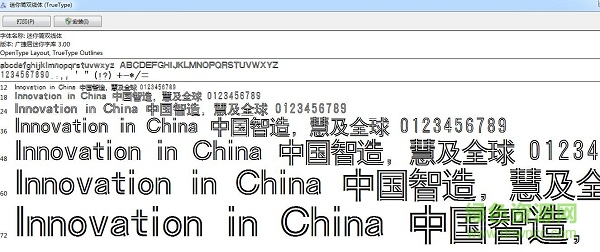
jsuanxian
jsuanxian字體是一款個(gè)性十足的迷你簡(jiǎn)雙線體字體,所有線條都是雙層,黑白均勻,結(jié)構(gòu)端正,非常醒目,適合用在各種廣告設(shè)計(jì)方面,有需要者歡迎免費(fèi)下載!
字體的筆畫(huà)差異
筆畫(huà)是字體構(gòu)成最基本的單位,筆畫(huà)的設(shè)定對(duì)于字體性格的表現(xiàn)也尤為重要,是線段還是塊面即使相同的字也會(huì)給人截然不同的感受。
jsuanxian
【曲vs直】
就像自由體操和拳擊,一個(gè)柔美靈活,一個(gè)剛勁力量。在字體里面,筆畫(huà)以曲線為主的話,就會(huì)給人飄逸柔和的感覺(jué),相反筆畫(huà)直來(lái)直往,包括轉(zhuǎn)角處多為折角,這樣的字體干脆利索,有速度和力量感。
【粗vs細(xì)】
字重的粗細(xì)就能會(huì)自然而然聯(lián)想到“厚重”和“輕盈”,只要記住筆畫(huà)越細(xì)字體越輕盈,筆畫(huà)越粗就更具分量感。